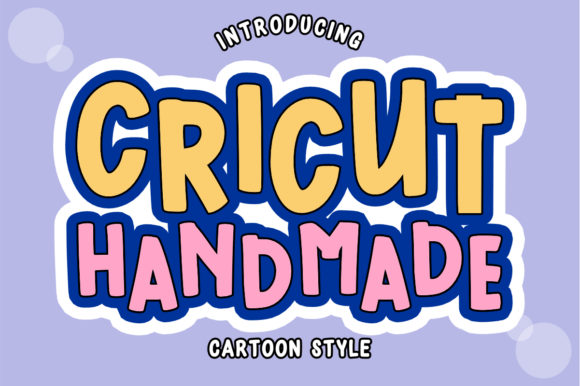
Cricut Handmade
Mencari elemen reka bentuk yang sesuai boleh menjadi mencabar, tetapi Cricut Handmade menawarkan koleksi luar biasa yang menaik taraf karya anda serta-merta.
Dicipta dengan ketepatan, Cricut Handmade menyediakan vektor yang bersih, tipografi yang licin dan lesen komersial untuk ketenangan fikiran.